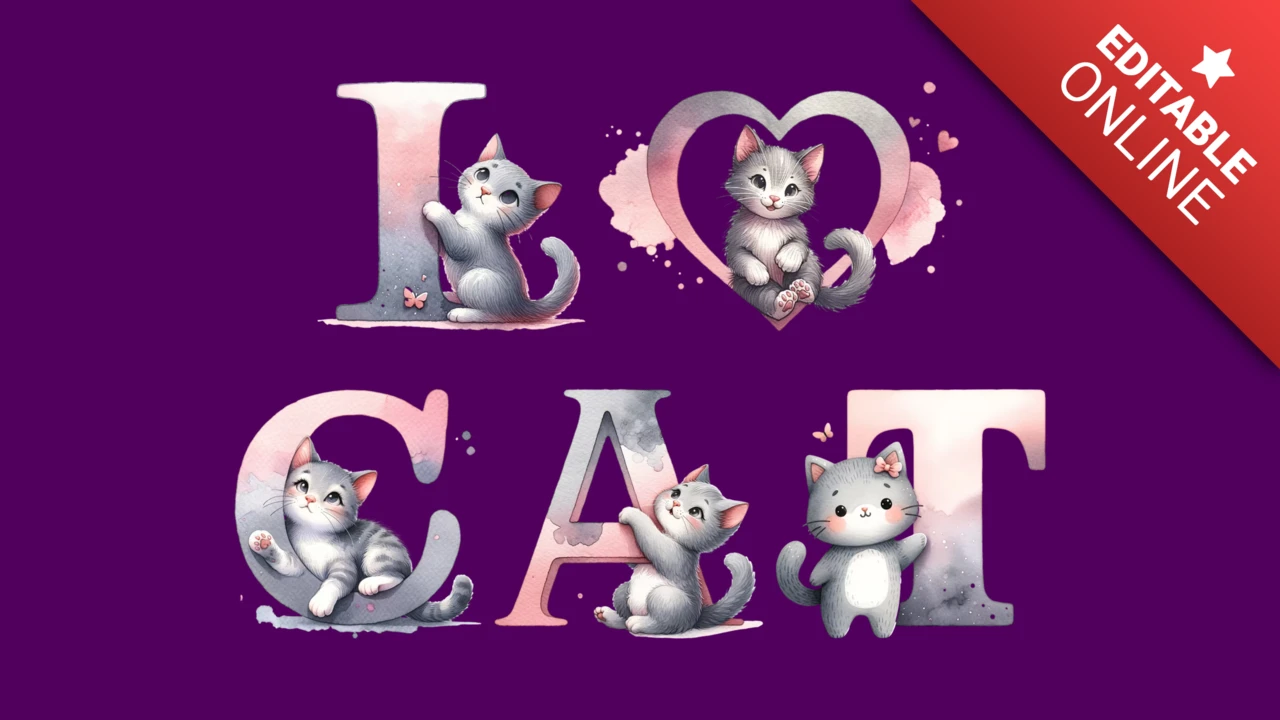
Kitten watercolor alphabet font
Découvrez le charme de notre dernier effet de texte, parfait pour apporter une touche ludique et artistique à vos créations grâce à son alphabet aquarelle unique sur le thème des chats. Idéal pour les projets créatifs !